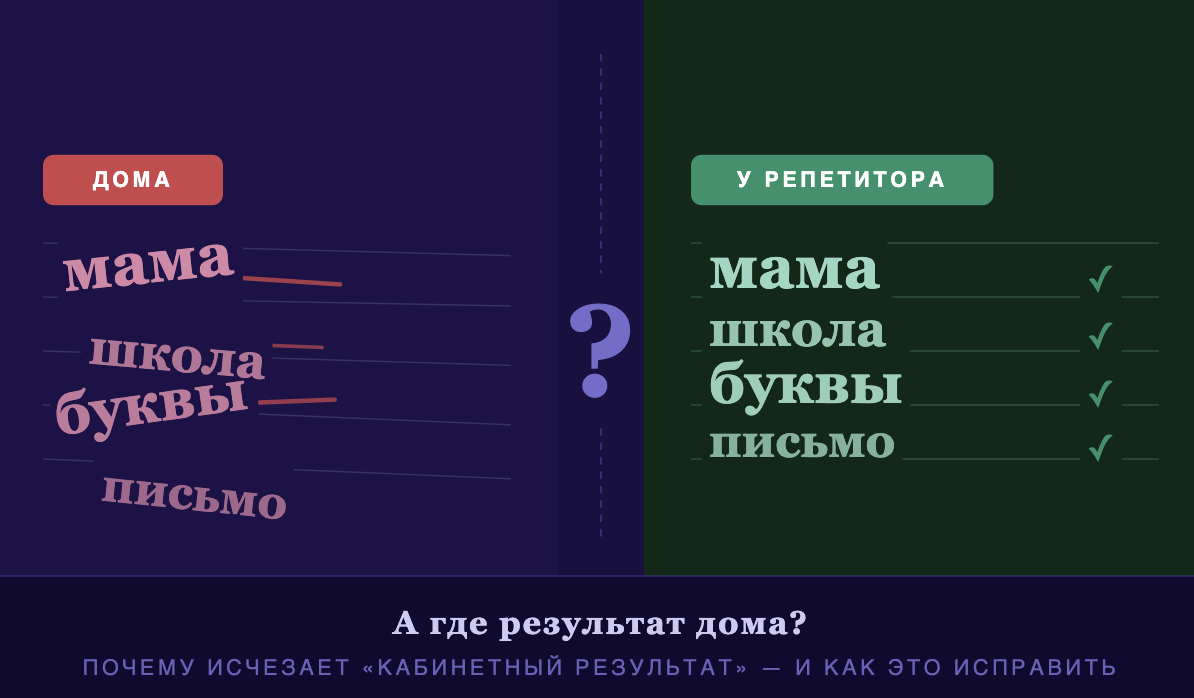
Коррекция почерка у детей: почему «кабинетный результат» исчезает
И как создать устойчивый красивый почерк, который останется навсегда
Занимались с репетитором — в тетрадях красота. Дома — снова каша. Знакомо? Я — психолог, педагог и многодетная мама — объясню, почему это происходит и как сделать так, чтобы красивый почерк у ребёнка остался навсегда.
Жёсткие правила, прописи, механическая тренировка. Результат есть только в кабинете — дома всё рассыпается.
Адаптируется под ребёнка, растёт вместе с ним. Результат устойчив в школе, дома и на диктанте.
Почему обычные прописи и механические методики не работают
Вы находите хорошего специалиста по коррекции почерка у детей. Начинаются интенсивные занятия — и в кабинете буквы становятся ровными, аккуратными. Вы выдыхаете с облегчением. Но как только ребёнок возвращается за домашний стол или пишет диктант в классе, магия бесследно исчезает.
В профессиональной педагогической среде это называется «кабинетным результатом». В кабинете результат есть, за его пределами — нет.
Современные дети живут в плотной цифровой среде, их внимание устроено иначе. Искусственно привитый навык письма, не подкреплённый внутренним смыслом, рассыпается при первом же школьном стрессе или увеличении скорости диктанта.
Что такое «живая экосистема» для обучения письму детей
Чтобы получить устойчивый результат, который останется с ребёнком навсегда, нужна комплексная живая экосистема. Это подход, который растёт вместе с учеником, бережно адаптируясь под разные возрастные ступени.
Знакомство с движением, развитие руки, игровые упражнения без давления
Базовые элементы письма, правильный захват ручки, первые буквы
Автоматизация графического навыка через творческие форматы
Индивидуальный почерк, скорость, устойчивость под нагрузкой
Как превратить развитие навыка письма в игру и творчество
Вот как работает экосистема на практике. Если нам нужно тренировать графический навык — мы не просто пишем слоги. Мы отправляемся в «Почерк-квест»: дети путешествуют по мирам, изучают роботов, открывают «12 дверей». В процессе игры они легко переводят печатные буквы в письменные и создают личную книгу-алгоритм.
Другой формат — настенный календарь. Ребёнок каждый месяц пишет и оформляет новую страницу. За год — 12 уникальных страниц на стене. Он наглядно видит, каким было его письмо год назад и каким стало сейчас. Развитие навыка письма у детей происходит естественно — через интерес, творчество и регулярную практику.
Как добиться устойчивого результата в исправлении почерка у детей
Только внутри такой экосистемы возможна настоящая автоматизация письма. Ребёнок становится способен писать 10–20 минут без перерыва, не чувствуя усталости. Его темп возрастает, почерк ребёнка становится ровным и стабильным.
Молодая учительница Даша на протяжении четырёх лет начальной школы мягко внедряла элементы «живой» методики в уроки. Два раза в неделю дети практиковали письмо через творчество и игру.
70%учеников пришли к четвёртому классу с красивым, устойчивым, индивидуальным почерком.
А чтобы результат не потерялся при переходе в стрессовый пятый класс — заранее готовились летние тетради и проводились разговоры с родителями. Экосистема не бросает ребёнка.
Почему ребёнок не хочет писать и как вернуть любовь к письму
Не ищите спасения в монотонных прописях и не расстраивайтесь, если «кабинетный результат» быстро исчез. Это не ваша вина и не вина ребёнка.
Ищите среду, где письмо наполнено смыслом, где оно живёт и развивается вместе с ним. Когда ребёнок становится творцом собственных книг и календарей, его навык письма становится по-настоящему прочным и устойчивым.